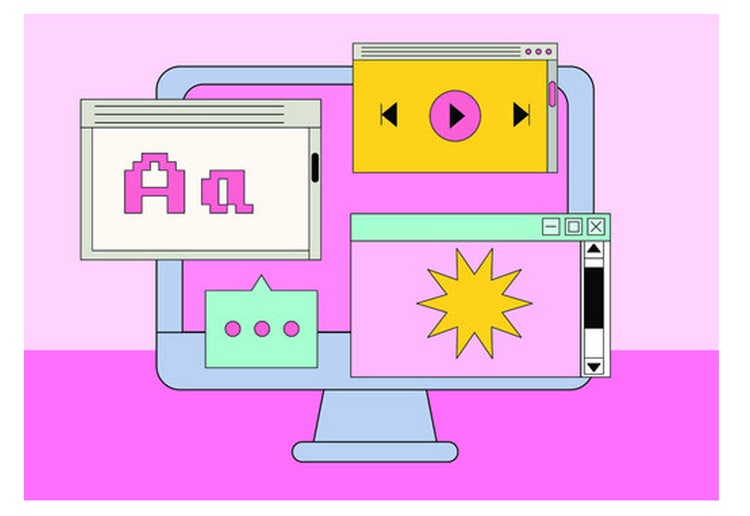
A escolha da fonte certa é essencial para qualquer projeto de design. Neste post, vamos explorar a história das fontes, o impacto delas no design, como escolher a opção ideal e onde encontrar fontes gratuitas de alta qualidade. Você também aprenderá como instalar essas fontes em seu computador para usá-las em seus projetos.
Como surgiram as fontes de textos?
As fontes têm uma história rica que remonta à invenção da escrita. Inicialmente, os caracteres eram desenhados à mão em pedras ou pergaminhos. Com o tempo, a criação da imprensa por Johannes Gutenberg no século XV revolucionou o uso das fontes, permitindo a reprodução de textos em larga escala. Desde então, elas evoluíram com o surgimento de novas tecnologias, como a tipografia digital, que democratizou ainda mais o acesso a diferentes estilos tipográficos.
O impacto de uma fonte no design.
A escolha da fonte pode transformar completamente a percepção de um projeto. Ela é capaz de transmitir emoções, valores e a identidade da marca. Por exemplo, fontes serifadas passam uma sensação de tradição e confiabilidade, enquanto fontes sem serifa transmitem modernidade e clareza. Um design com a fonte errada pode parecer amador, enquanto o uso adequado de tipografia pode elevar o impacto visual e a comunicação da mensagem.
Qual fonte escolher?
Escolher a fonte ideal depende do contexto e do objetivo do projeto. Por isso, sempre leve em conta o seguinte:
- Qual é a mensagem que eu quero transmitir?
- Quem é o meu público-alvo?
- Onde essa fonte será usada (impresso, digital, logotipo)?
Para designs formais, fontes serifadas como Times New Roman podem ser apropriadas. Para um apelo mais moderno, fontes sem serifa como Helvetica ou Roboto são boas opções. Se o projeto exige criatividade ou informalidade, fontes decorativas ou manuscritas podem ser ideais em conteúdos de vídeos, por exemplo.